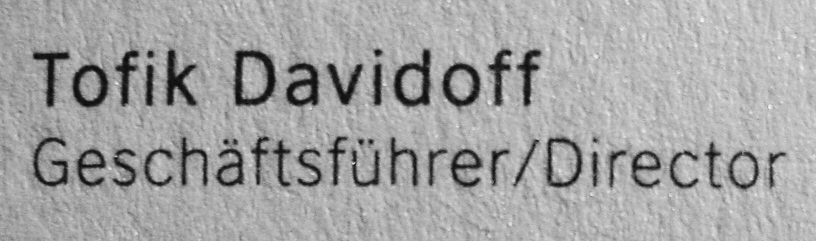
Sans in Richtung Franklin/News/Trade Gothic?
kennt jemand diese Sans hier?
(sorry, ein besseres Bild habe ich nicht)
IMO geht sie in Richtung dieser amerikanischen Groteskschriften, ist es aber nicht ganz.
Noch ein paar weitere Details:
die 1 hat keine Serife am Fuß
die 7 hat keinen Haken am oberen Querstrich
das R hat ein gerades Bein
der Winkel beim M geht nicht bis zur Grundlinie
Außergewöhnlich finde ich die ä-, ü-Pünktchen, das "riecht" nach einer alten Grotesk. Beim ersten Draufsehen hatte ich an die Corporate S gedacht, die es aber natürlich nicht ist.
das sieht aus wie eine Visitenkarte oder ein Briefkopf. Kannst Du nicht einfach mal versuchen dort anzurufen und dadurch an den Grafiker ranzukommen? Manchmal hilft das. Ich hatte vor einiger Zeit eine ähnliche Schrift gesehen (vielleicht ist es sogar diese?) und dachte an die Akzidenz Grotesk Old Style ... aber die ist es natürlich nicht. Leider hatte ich damals keine Adresse zum nachhaken.
Ja, das Gefühl, dass es eine alte Fotosatz-Schrift sein könnte beschlich mich auch schon. Corporate S ist aber als Alternative eine gute Wahl und passt stilistisch wesentlich besser, als die arg pragmatischen und wenig eleganten amerikanischen Schriften.
Ja, manchmal, aber nur manchmal, hilft das.
... in diesem Fall aber leider nicht. Grafiker und Drucker sind nicht mehr greifbar und der Kunde möchte gerne die gleiche Schrift wie früher.
notfalls nimmst du eine trade gothic oder eine news, wird der kunde kaum mitbekommen ;)
Nee nee, das ist kein guter Stil Kundenwünsche kommentarlos zu ignorieren, mit einer Attitüde von "das sieht der eh nicht". Gerade in diesem Fall würde jeder Laie spätestens bei der fetten Serife der 1 von Trade oder News Gothic den Unterschied erkennen. Meistens würde ein Kunde in so einem Fall zwar wirklich nichts bemerken, aber es kann auch ganz schnell dazu führen, dass sich die Leute verarscht fühlen und sich das Verhältnis, gerade bei Neukunden, ein ganz klein wenig eintrübt. :wink:
Ich hab nun jedenfalls die Corporate S genommen, finde das alles sehr ordentlich aussieht und warte mal ab, was für ein Feedback kommt.
hä? aber die corporate S ist es doch auch nicht. :?
Ja. Aber Foniq hat nach seiner Aussage dem Auftraggeber mitgeteilt dass die verwendete Schrift nicht identifizier- und damit auch beschaffbar ist und er deshalb die Corporate S genommen hat. Das erscheint mir fair und sinnvoll zu sein.
ja, hätte ich auch so gemacht. mit kaum mitbekommen mein ich ja nicht das es hinter dem rücken des kunden geschen muss. sondern das man halt eine ähnlich schrift nimmt, wo der kunde den unterscheid eh nicht merkt, man ihn aber darauf hinweisst.